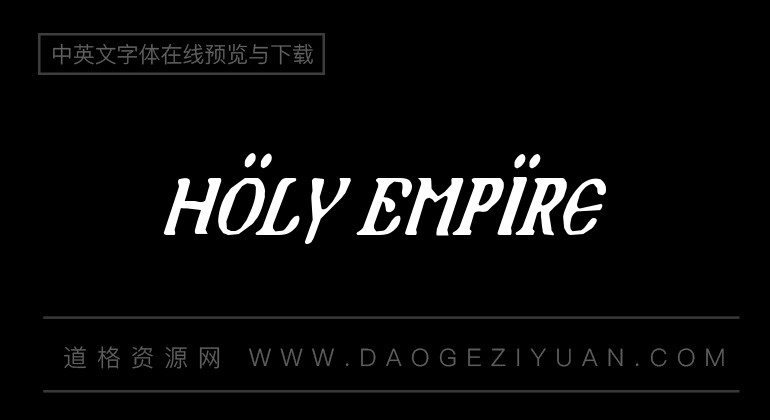
Holy Empire
Holy Empire 是一款由著名设计师Alessio Laiso创作的英文字体,它具有经典的旧式英文字体特征,细节丰富,体现出古典优雅的风格。它有着柔和的笔画,圆润的字形,以及精美的细节,具有较高的可读性和较强的视觉效果。它可以用于书籍封面,广告海报,海报,标志,网页设计等,能够更好地展示您的设计作品。
Holy Empire是一款非常不错的手写艺术字体,具有很好的视觉感,适合于文化类的宣传设计、商业类品牌的广告和产品包装设计以及个性化文字排版等较多场景。